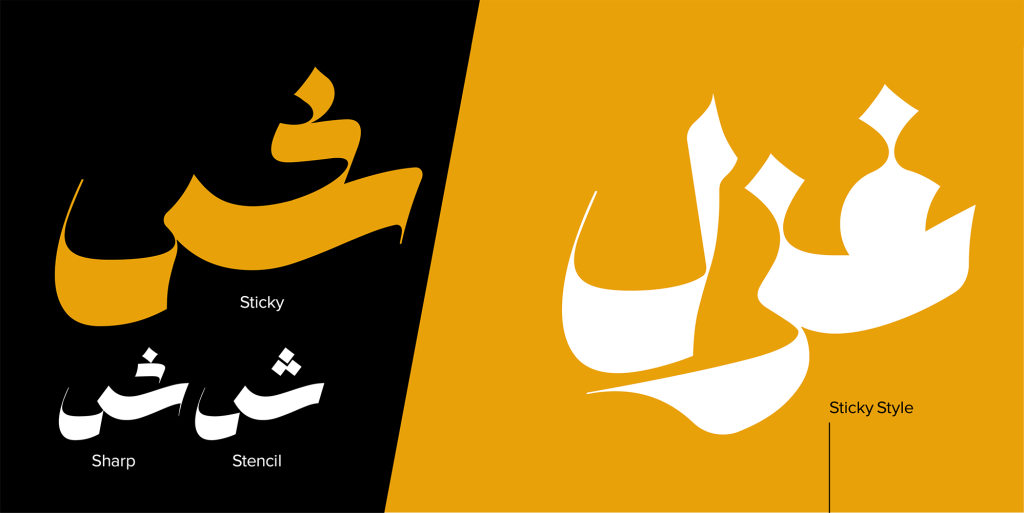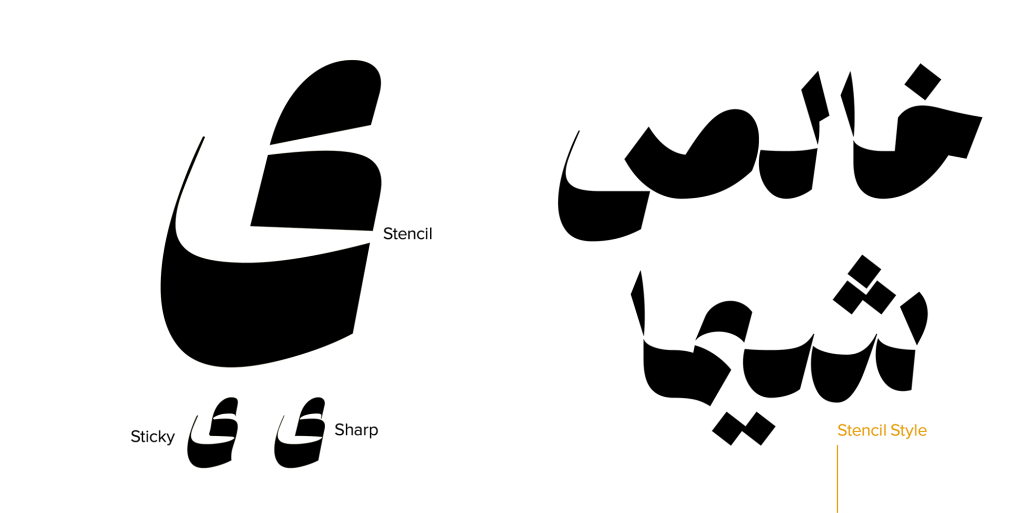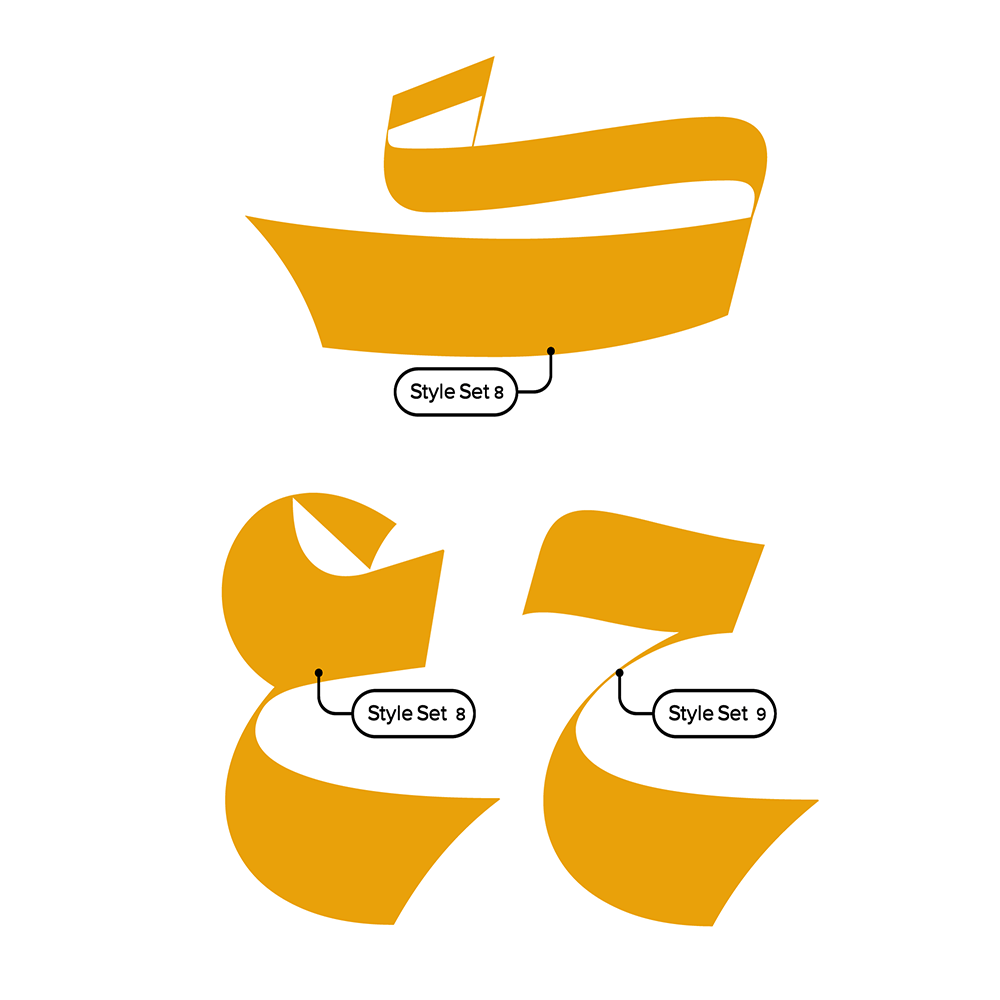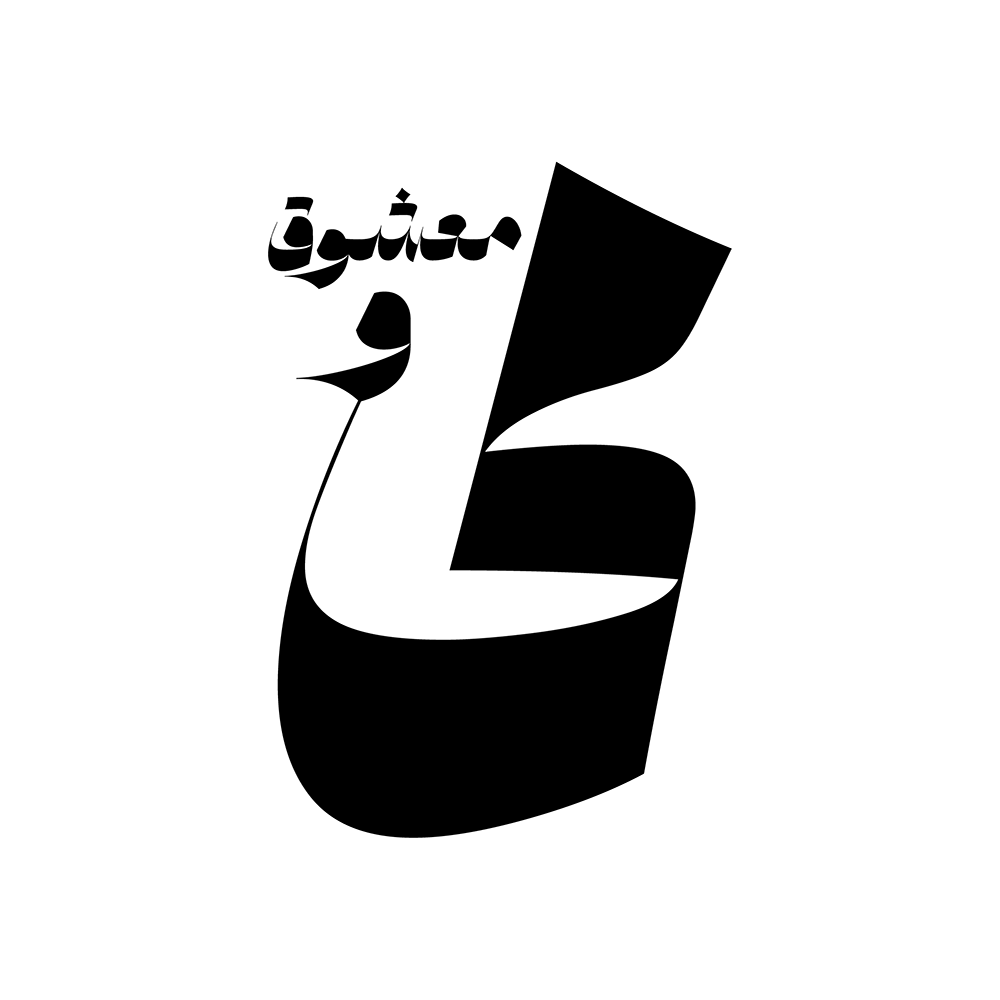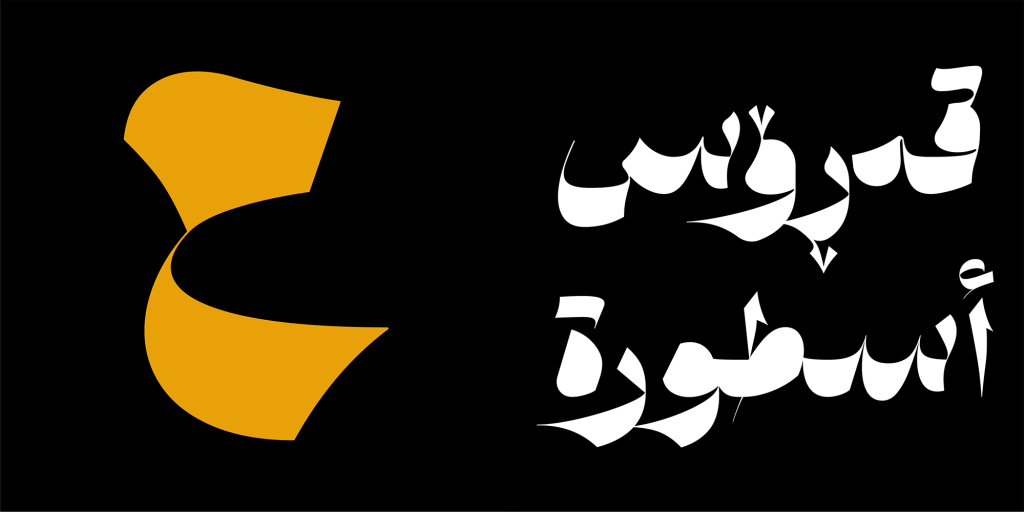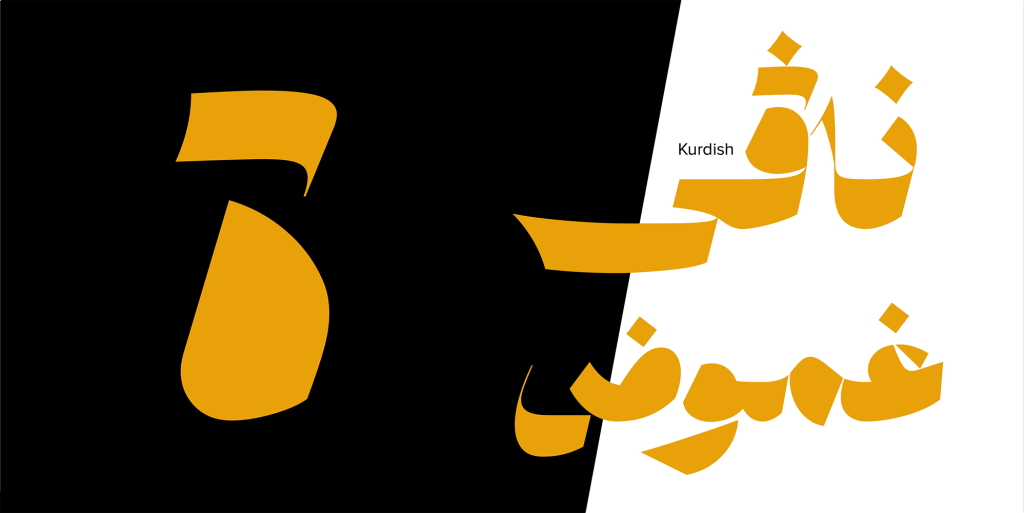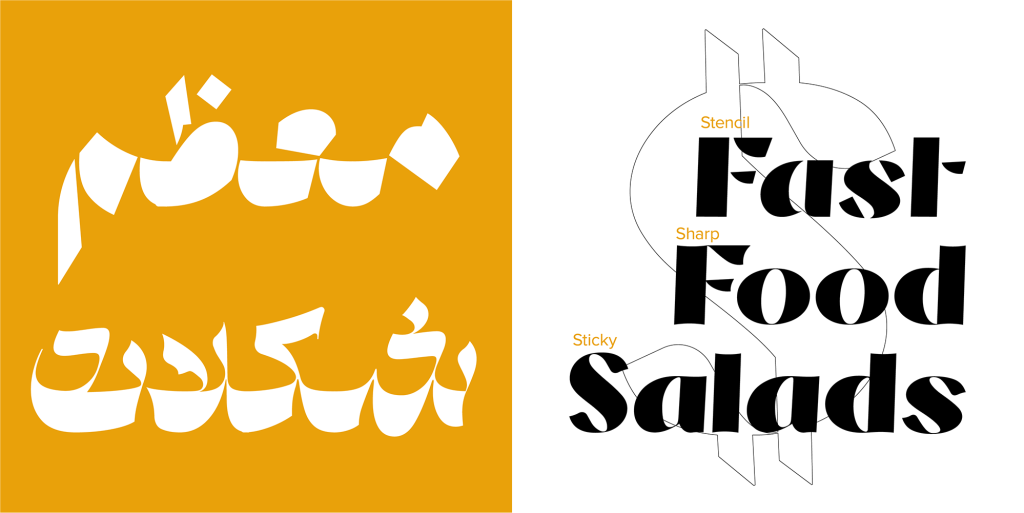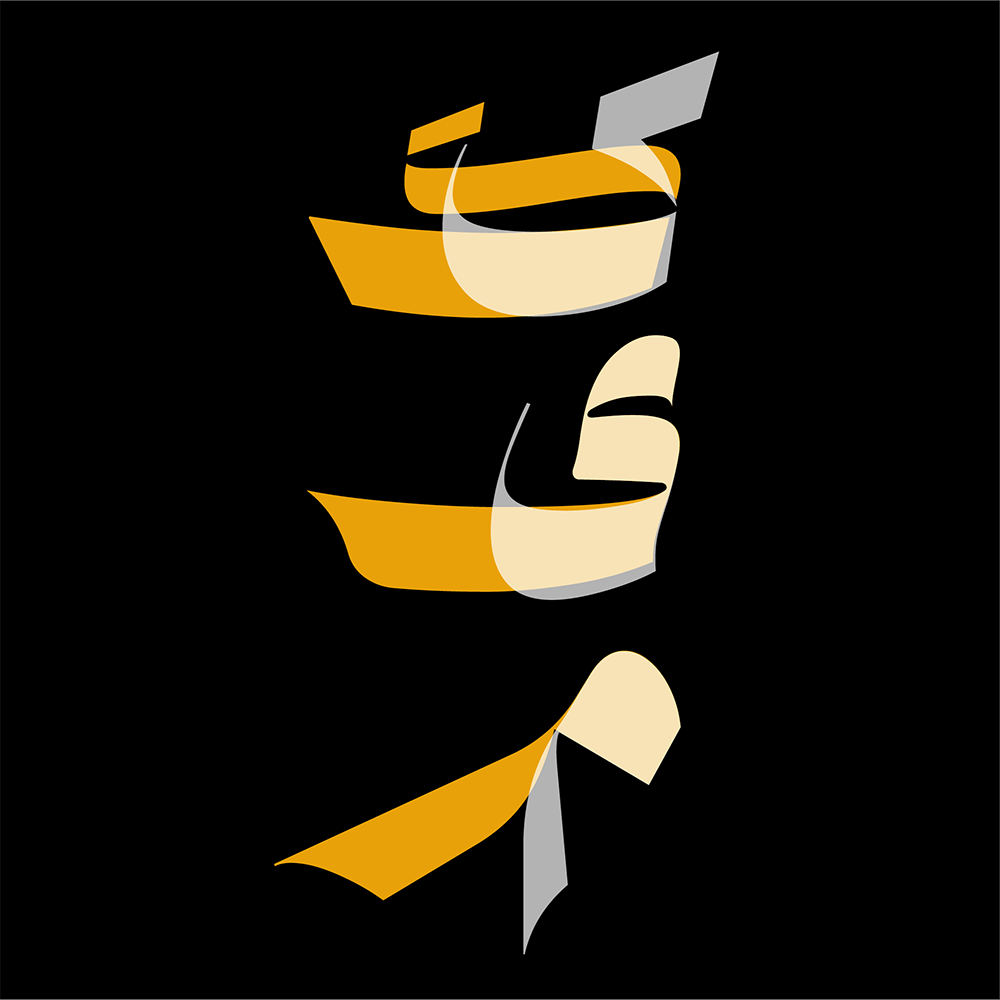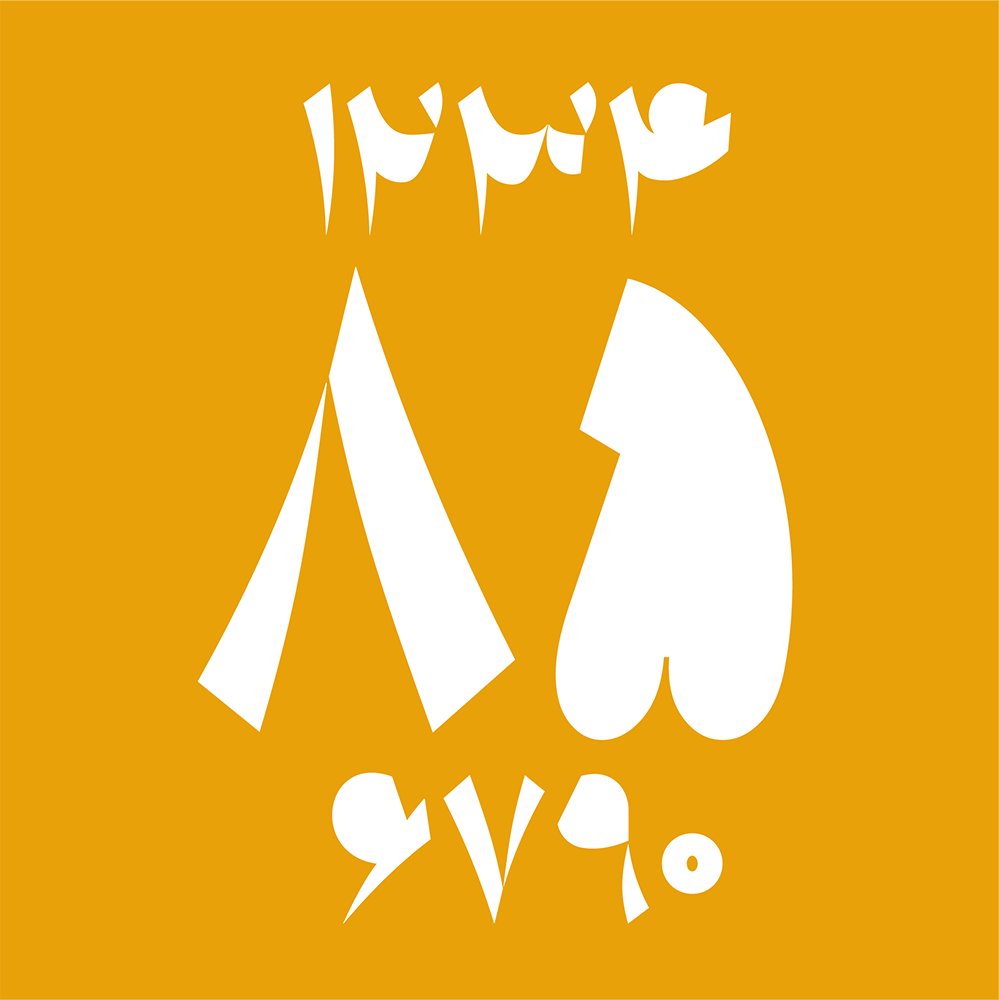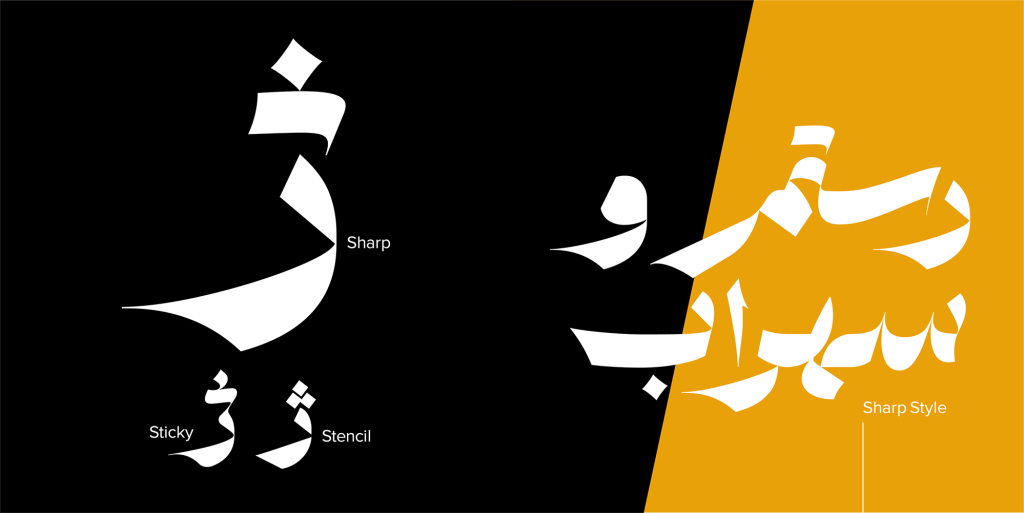
فونت شیوه – قلمی برای دیده شدن
فونت شیوه تایپ فیسی از خانواده دست نویسه که دارای 3 استایل یا همون سبک نوشتاریه. این قلم ساخته شده تا بدرخشه و خود نمایی کنه و هدف از ساخت این تایپ فیس هم همین بوده اصلا مناسب متن نیست و فقط برای عناوین کوتاه به درد میخوره. اگه دنبال یه فونت تیتر برای پوستر، کاور، برند یا طراحی جسورانه هستی، این قلم یکی از بهترین هاست.
اگه کمی توی فرم های ساختاری این قلم دقت کرده باشین مطمئنا متوجه تغییرات بنیادین و جسورانه شدین. در اصل شیوه الهامش از فرمهای نسخ سنتی بوده ولی به قدری دگرگونی پیدا کرده که تبدیل به یه فونت خاص و گرافیکی شده. دیگه خبری از تعادل و خونسردی نیست و همه تلاش تک تک اجزای تشکیل دهنده این تایپ فیس یک چیزه، دیده شدن.
شیوه دارای 3 استایل می باشد
Sticky که فرمهاش نرم و کشدارن و یه حس عجیبی بین سنتی و دیجیتال داره.
Sharp با لبههای تیز و محکم؛ جدی، عصبی و آمادهی درگیری.
Stencil کاملاً هندسیه و طراحیش دقیق و ساختاریافته است. خطوط صاف و برشهای مشخصی داره که خیلی جدی و محکم توی چشم میزنه.
امکانات فراوان و پشتیبانی از زبان های مختلف
تایپ فیس شیوه شخصیتی جسور و بی باک دارد. در دیزاین این فونت تلاش براین بوده تا اشکالات فنی و زیباییشناختی فونت برطرف شود و لیگیچرهای مناسب و جدید برای آن طراحی شود. برای بسیاری از حروف، گلیفهای جایگزین طراحی شده است، این قابلیتها به شما قدرت انتخاب و ایجاد تنوع در تایپوگرافی را میدهد.
شیوه با پشتیبانی از زبان های مختلف از جمله کوردی، انگلیسی، اردو ، عربی و …دارای ویژگی چند زبانی هم می باشد. در تصاویر زیر می توانید نمونه هایی زیبا که برای شما عزیزان مهیا نموده ایم استفاده کنید.